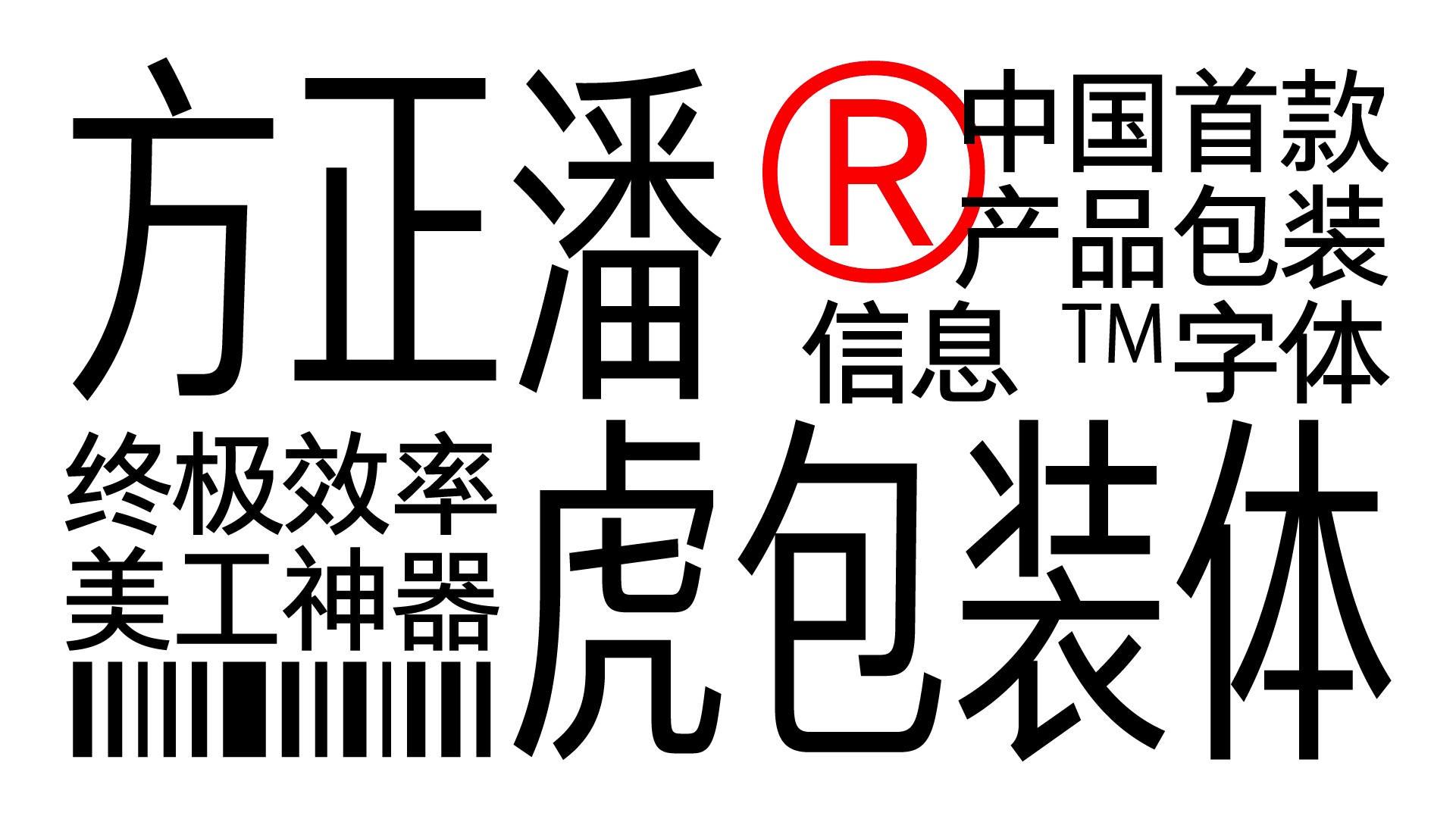
2025年7月18日,方正字库联合潘虎设计实验室,发布专为包装行业深度定制的系统性字体解决方案——“方正潘虎包装体”。作为业内首款针对包装设计制作痛点打造的字体产品,方正潘虎包装体严格遵循国家包装法规标准,深度融合智能排版技术,为行业高质量发展提供了强有力的技术支撑。该字体的发布,标志着包装设计领域正式迈入标准化、智能化、高效化的崭新时代。
发布仪式上,北京北大方正电子有限公司总裁兼方正字库事业部总经理张建国出席并致辞。群玉山咨询董事长兼首席策略官马晓波,以《设计与社会公共资产》为题发表主题演讲,揭示顶尖品牌如何通过包装视觉,将商业策略转化为公共价值。同时,潘虎设计实验室产品和包装设计师潘虎,方正字库设计总监汪文,以及方正字库高级字体设计师何诗旸发表主题演讲,深入阐释了方正潘虎包装体的设计理念、核心价值与广泛适用场景,系统回应了包装设计师长期面临的共性难题,共同见证包装字体发展的重要里程碑。
包装是品牌与消费者对话的“第一界面”,直接影响产品市场表现。然而,现有字体解决方案的局限性,迫使设计师陷入机械性劳作泥潭:中西文字高偏差需逐行修正,窄体压缩引发字形粘连,多语种混排合规性难保障,特殊材质印刷失真频发。这不仅蚕食设计师的创意时间,更可能导致产品上市周期延长。产品和包装设计师潘虎先生指出:“方正潘虎包装体的诞生,从根本上解决了这一核心困境。其创新的中西文字高一致性设计,结合智能排版系统,能够显著提升设计效率,确保视觉呈现的统一规范与合规要求,为设计师释放宝贵创意空间。”
方正潘虎包装体立足包装设计的实际需求,在字体设计、符号集成与工具开发层面进行了系统性创新。该字体家族结构完备,以5档精细字重(Light至Medium)与6级灵活字宽(50%-100%)组成30款字体矩阵,覆盖中文、西文、包装专用符号、条形码、二维码等,用户还可选择可变字体,精准适配食品、饮品、快消等主要包装应用场景,助力用户快速便捷地实现小空间精细排版。方正潘虎包装体严格遵循国家标准进行合规性设计,其核心创新点在于实现了中西文字符的视觉高度统一,严格匹配国家标准(如GB 7718-2011规定的1.8mm最小字高等关键参数),支持GB18030-2022 L2超大字符集,包含27780个汉字,基本解决配料表、生僻字、地名等信息缺字问题。为全面提升设计效率,方正潘虎包装体同步配备了智能排版插件系统。该插件支持智能字号设定、自动行距匹配,同时集成运输标识、环保标志、安全警示等包装专用符号库,并可实现条形码与二维码一键生成,便于设计师快速合规调用。方正字库设计总监汪文先生强调:“在方正潘虎包装体的产品架构设计中,我们不仅高度关注字体在多元场景下的适用性,更着重提升了字体与设计软件生态的协同效率,使其超越传统字体范畴,成为具备强大生产力的智能化设计工具。”方正潘虎包装体支持拉丁文、西里尔文、希腊文、越南文等多语种体系,并在设计风格上保持中西文字符协调统一。方正字库高级字体设计师何诗旸先生表示:在西文设计时,特别引入“油墨陷阱”设计理念,使其和中文整体风格完美融合的同时,确保小字号印刷时笔画清晰、不粘连,全面提升可读性和适配性,有效解决品牌全球化进程中的字体风格不一致、输出质量不稳定的关键痛点。本次发布会上,方正电子正式向中国包装联合会设计委员会授权字体使用,标志着包装行业标准化用字建设迈出坚实一步。在消费者需求瞬息万变、品牌竞争日益激烈的当下,包装不仅是容器,更是品牌与消费者沟通的第一触点,是传递价值、塑造认知的关键载体。而包装字体的规范化、合规化,已成为保障品牌安全、规避法律风险、提升商业效率的基石。发布会上,清华大学美术学院教授王红卫、瑞幸咖啡副总裁申跃、徐福记国际集团品牌总经理蔡典儒、产品和包装设计师潘虎、方正字库设计总监汪文,以及方正字库高级字体设计师何诗旸出席了圆桌论坛,共同探讨如何以合规、安全的包装体为基石,敏锐捕捉并引领消费者需求变化,通过强大的包装视觉系统,为品牌注入持久生命力,驱动商业价值的增长。(方正潘虎包装体直播发布会圆桌论坛从左至右:方正字库设计总监汪文、瑞幸咖啡副总裁申跃、徐福记行销总经理蔡典儒、清华大学美术学院教授王红卫、产品和包装设计师潘虎、方正字库高级字体设计师何诗旸)方正字库直面行业长期痛点,携手潘虎设计实验室联合研发打造包装行业革命性产品——方正潘虎包装体,填补了我国产品包装信息字体的空白。通过中西文等高架构、50%-100%字宽矩阵、多语言适配、生僻字支持、印刷优化及智能插件,方正潘虎包装体首次实现包装设计的系统化、自动化、全球化三位一体,实现包装设计效率和美感兼容的整体跃升。未来,方正字库将持续携手行业先锋力量,深化合作创新,致力于构建全球化品牌体系下的字体视觉基础设施,不断推动中国包装设计产业在标准化建设、效率提升、美学表达及全球适应性等方面的全面升级,为中国品牌走向世界提供强大助力。